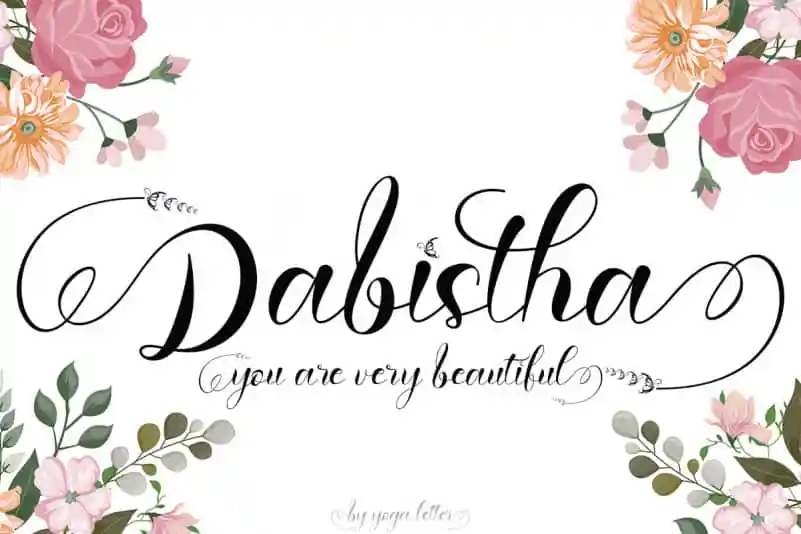
Esta fonte é chamada Dabistha Calligraphy Font. Ela vem da arte cuidadosamente criada do designer Yoga Letter, conhecida por sua beleza e qualidade elevadas. Este tipo de fonte enriquece qualquer trabalho com um toque elegante, perfeito para marketing de produtos, divulgação de negócios, criação de citações, convites nupciais, logotipos, marcações e atualizações em redes sociais durante o Natal. A Dabistha é uma fonte ideal para aqueles que buscam dar um toque especial a seus momentos especiais, seja no seu trabalho diário ou nas ocasiões mais significativas. Seja você quem está criando logotipos para uma marca ou simplesmente adicionando um toque único à sua mensagem pessoal, esta fonte oferece a oportunidade de expressar-se em maneiras elegantes e únicas.